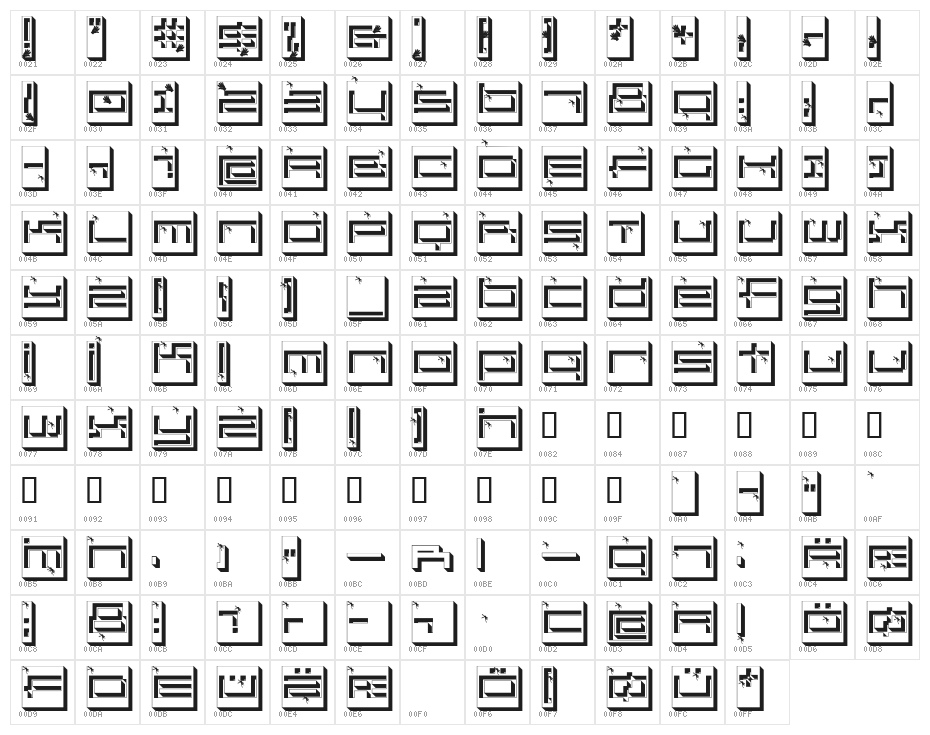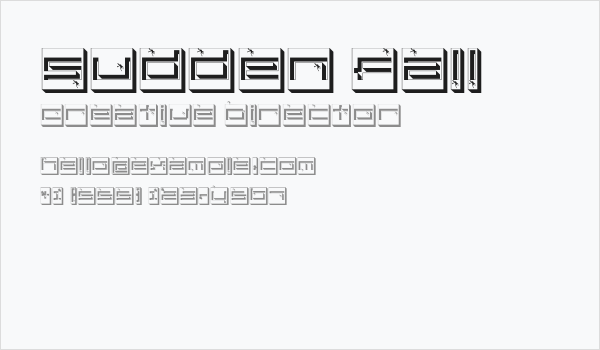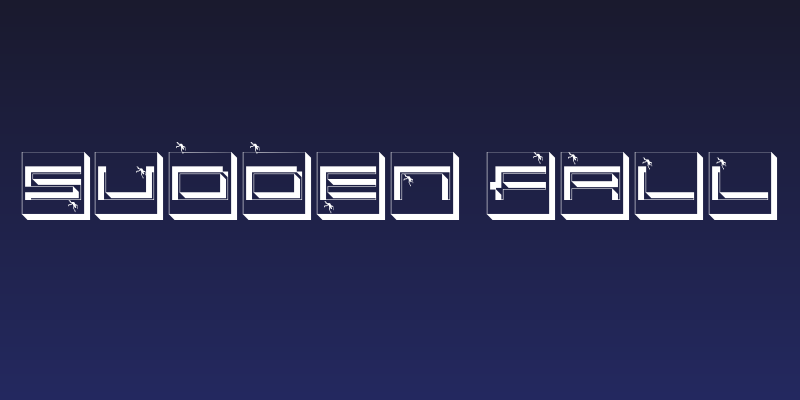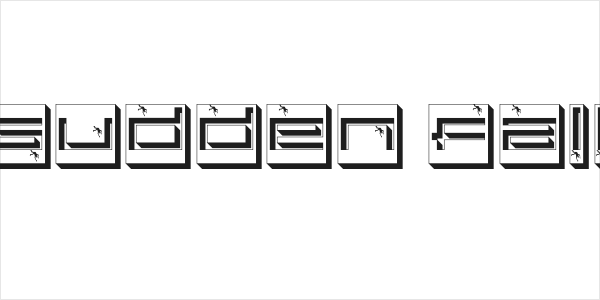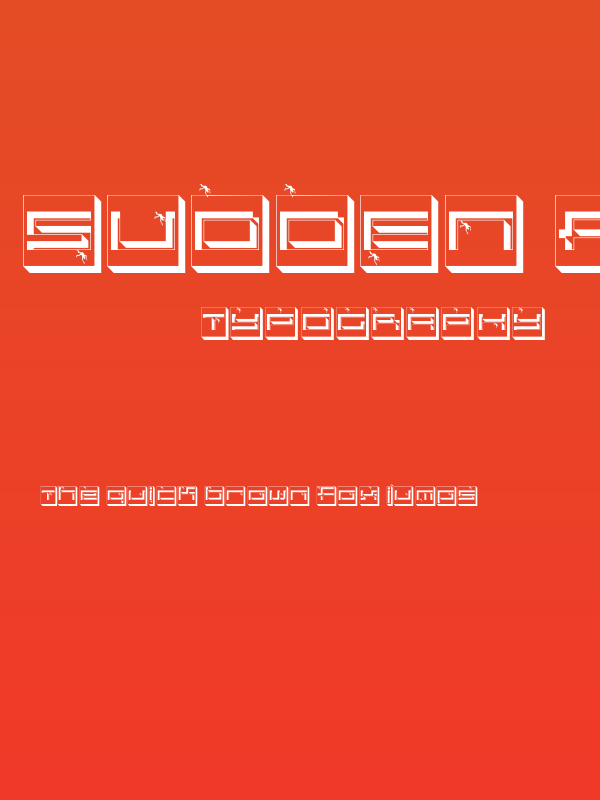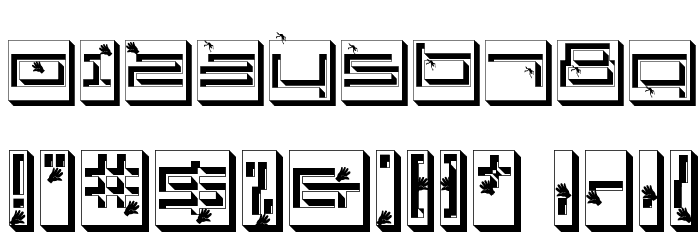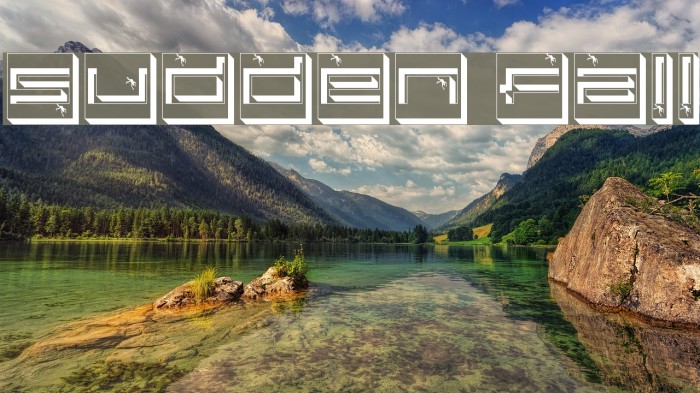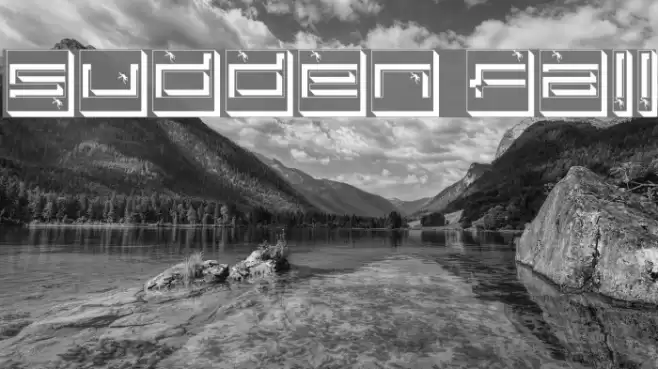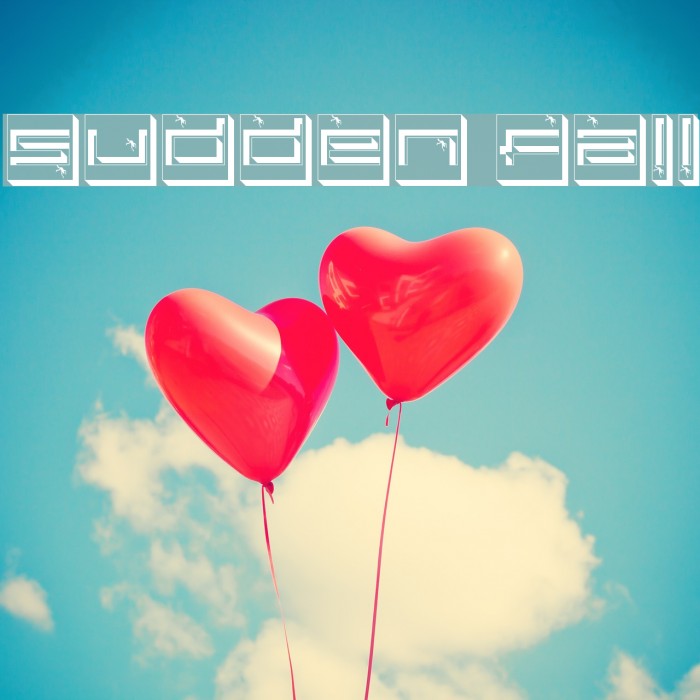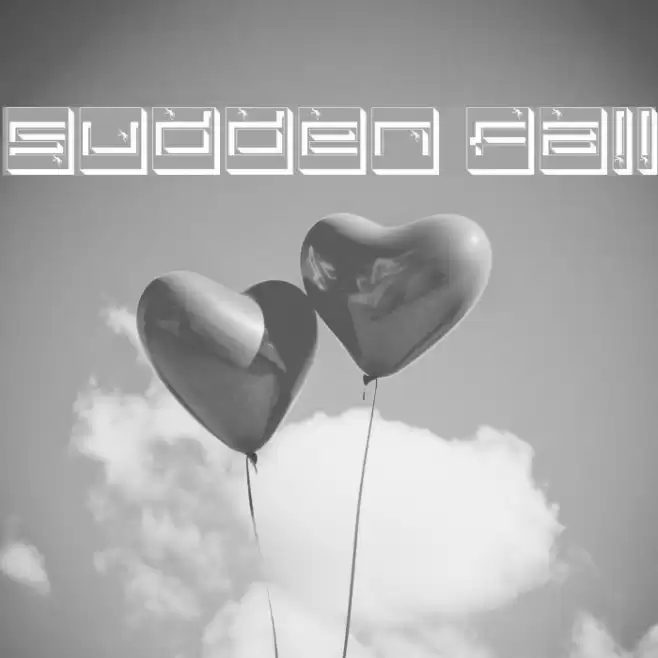
Sudden Fall Font
| Общий стиль | Modern, Decorative |
| Рекомендуемые проекты | Ideal for posters, album covers, video game graphics, and branding that requires a fun and dynamic look. |